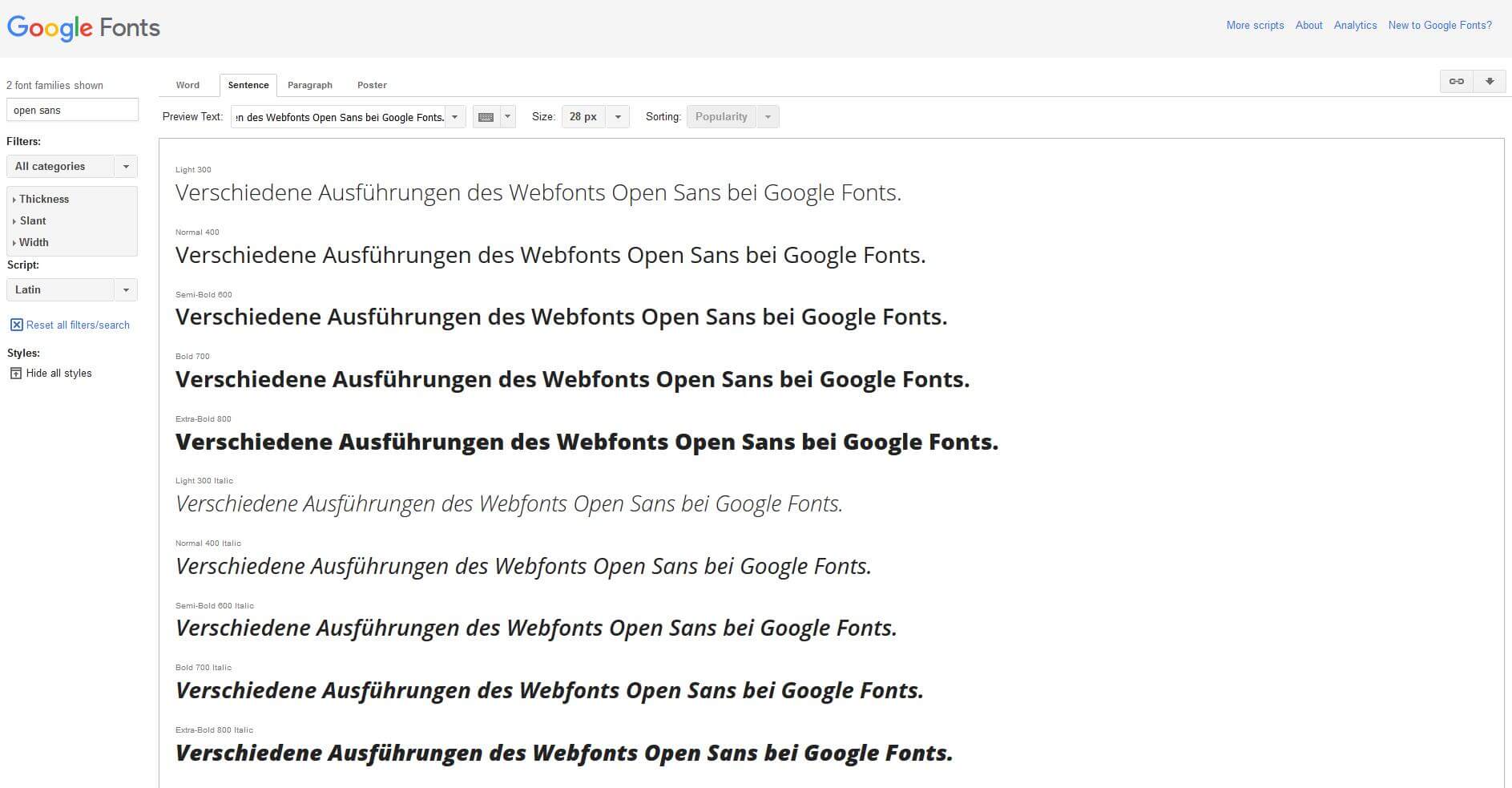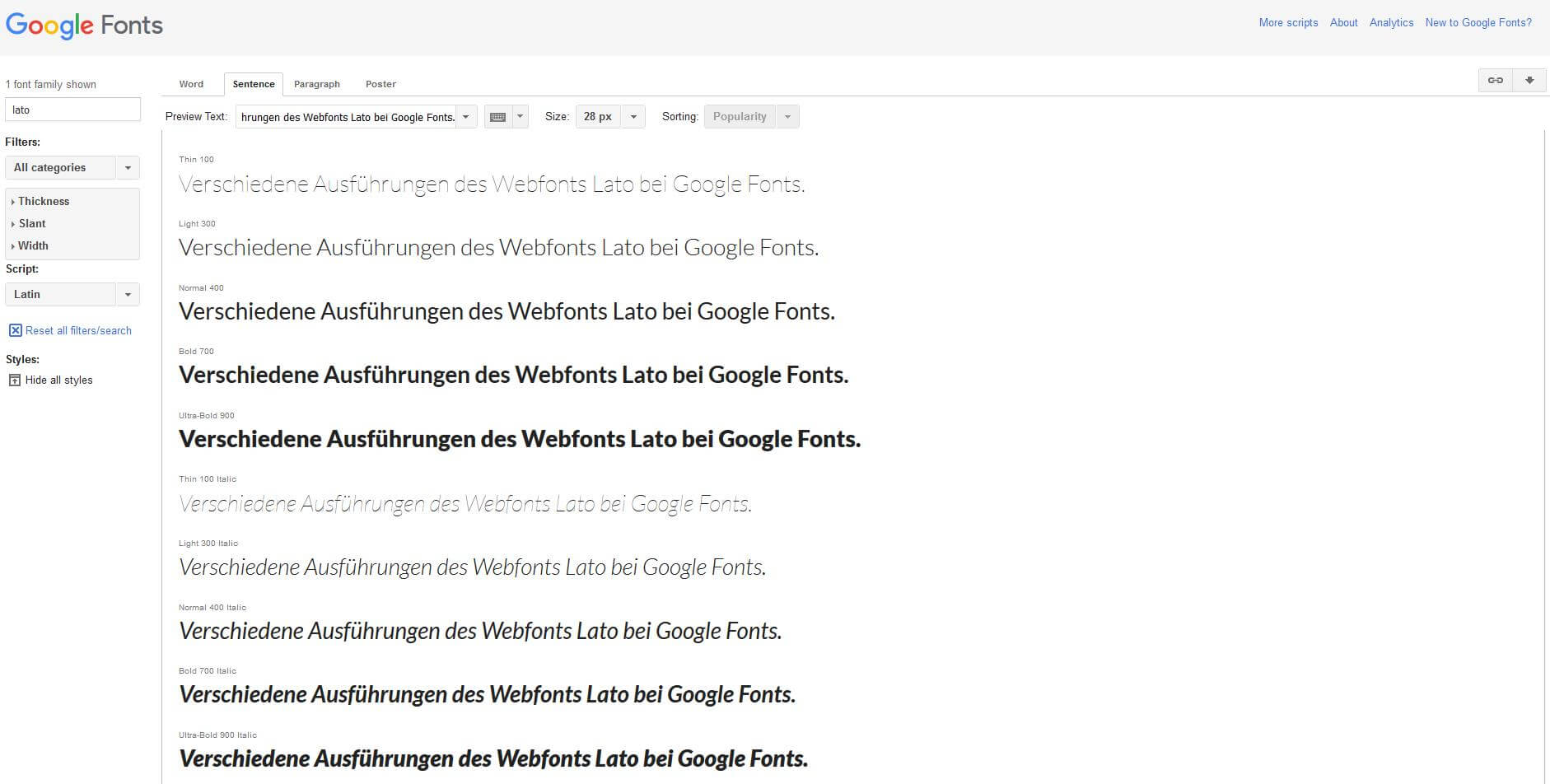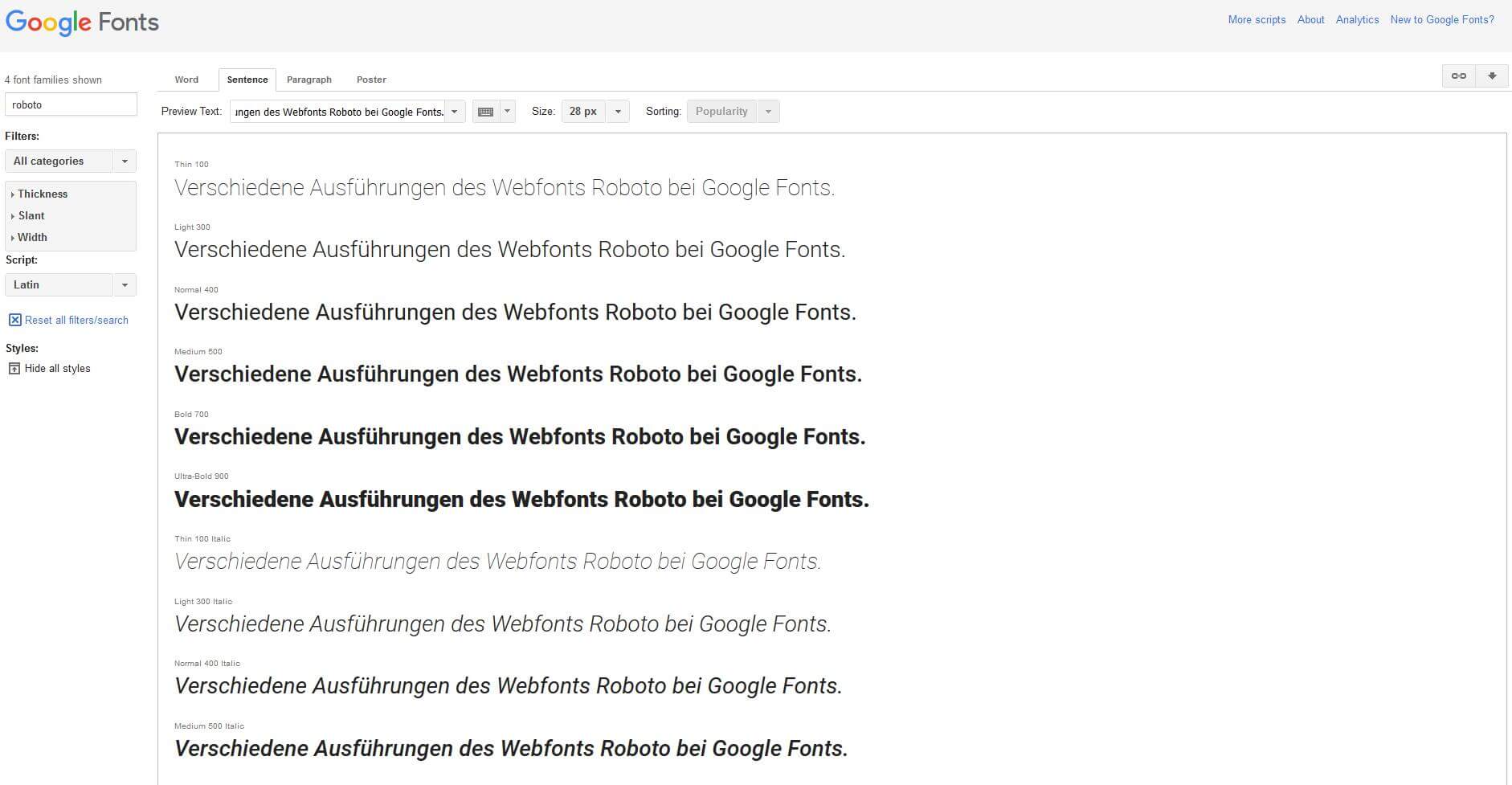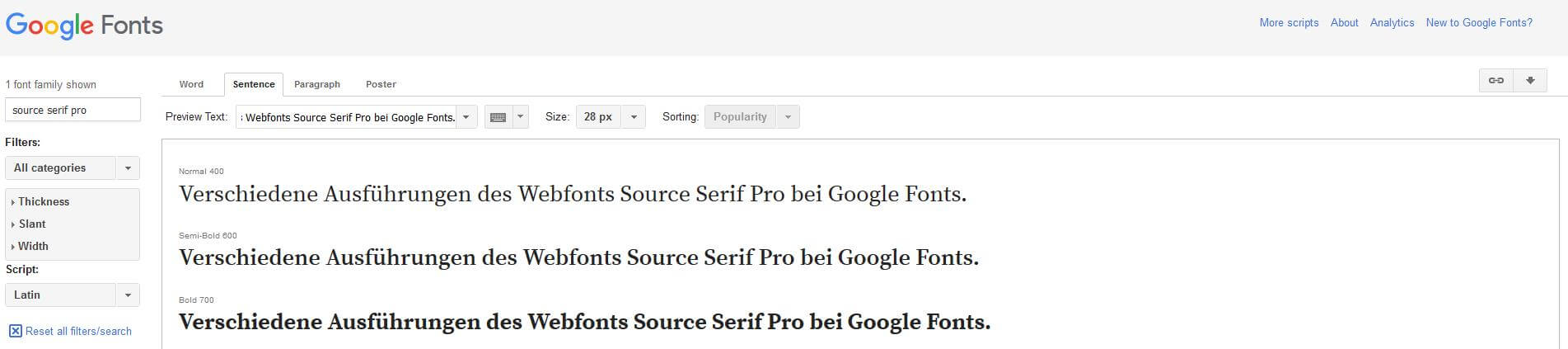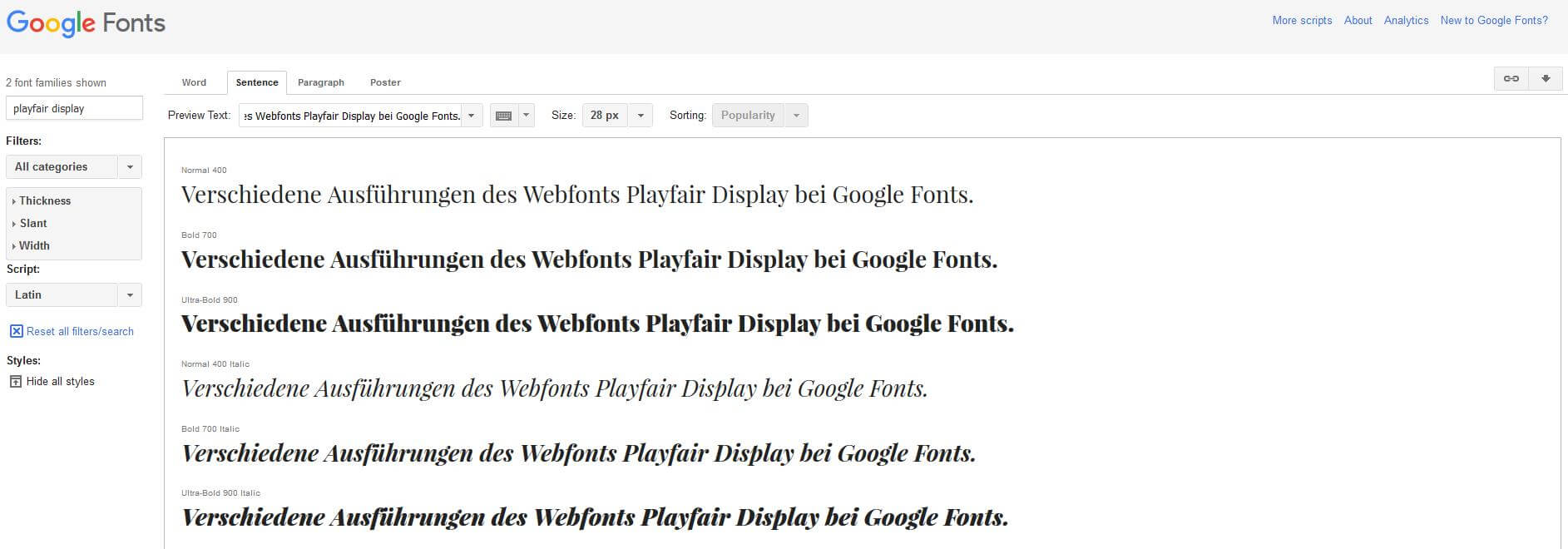
Typografie im Responsive Webdesign - Teil 2: Geeignete Schriftarten
Wenn Sie eine Schrift für Ihre responsive Website suchen, können Sie sich aus dem reichhaltigen Angebot an sogenannten responsiven Webfonts (reaktionsfähigen Schriften für Internetseiten) im Netz bedienen.
Kostenlose Webfonts fürs Responsive Webdesign
Webfonts eignen sich als Grundlage für die Typografie im Responsive Webdesign, da sie auf Vektorgrafiken basieren, die frei skalierbar sind. Beim Aufruf einer Webseite, die Webfonts verwendet, werden die Schriften von einem Server heruntergeladen und anschließend zur Anzeige im Webbrowser des Users umgesetzt. Reaktionsfähige Webfonts passen sich hierbei den Anforderungen des jeweiligen Browsers bzw. Anzeigegeräts an. Diverse Internet-Plattformen halten responsive Webfonts zum Download bereit – teils gratis, teils kostenpflichtig. Bekannte Anbieter von gebührenpflichtigen Schriftarten sind beispielsweise Adobe Fonts oder Fontspring, die mit einer großen Auswahl an bekannten Schriftarten, darunter vielen Klassikern, aufwarten.
Genauso können Sie aber auch auf das nicht weniger vielfältige Angebot an kostenfreien Webfonts zurückgreifen. Sammlungen freier Webfonts finden Sie z. B. bei Google Fonts, Font Squirrel oder DaFont. Nicht alle dort erhältlichen Schriftarten eignen sich für den allgemeinen Gebrauch: Einige sind zu verspielt oder ungewöhnlich und deshalb nur für spezielle Belange zu empfehlen; manche enthalten keine Umlaute oder andere Sonderzeichen – generell variiert der Zeichenumfang der Schriftarten, teilweise stark. Achten Sie daher darauf, dass Sie für Ihr Responsive Webdesign eine Schrift auswählen, die ausreichend viele Zeichen umfasst. Exemplarisch stellen wir Ihnen einige vielseitig einsetzbare Google Fonts für Ihre Website vor.
Webtypografie-Beispiele von Google Fonts
Die Plattform Google Fonts wird von vielen Webdesignerinnen und -designern als Quelle von Schriften für eine reaktionsfähige Typografie genutzt. 2010 ging die Seite online. Von Anfang an wurden ausschließlich kostenlose Open-Source-Fonts angeboten, die sowohl für nichtkommerzielle als auch für kommerzielle Zwecke genutzt werden dürfen. Sie haben die Auswahl aus über 1.900 verschiedenen Webfonts. Alle Fonts können Sie herunterladen und über einen Code in Ihren Webauftritt einbetten.
Open Sans
„Open Sans“ gehört zu den klassischen Standard-Webfonts. Es handelt sich um eine serifenlose Schrift mit klassischem, schlichtem Erscheinungsbild. Sie wurde von Steve Matteson entworfen und ist für die Nutzung im Web, für mobile Geräte und für den Printbereich optimiert.
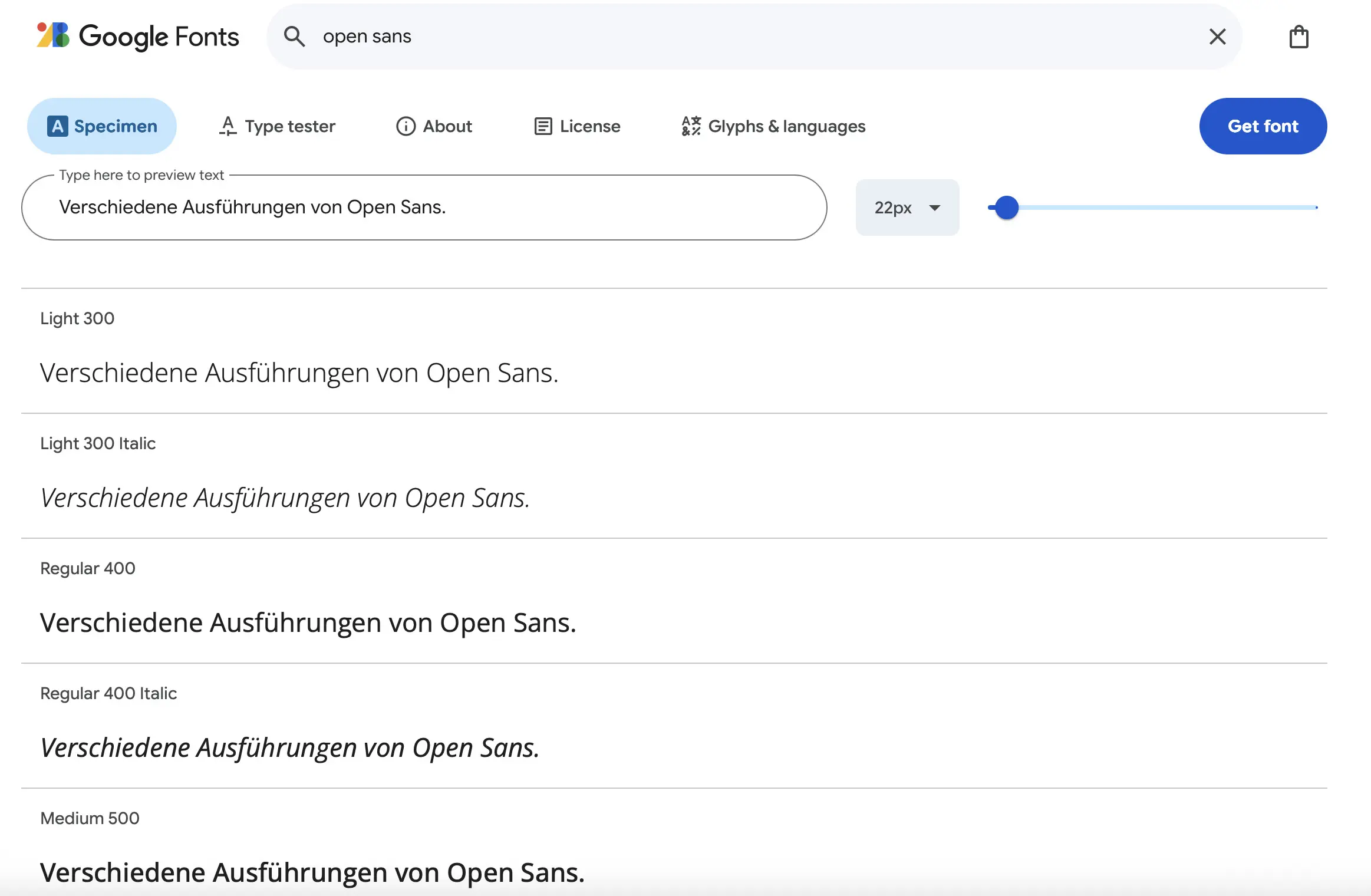
Lato
„Lato“ ist eine weitere populäre Schriftart ohne Serifen. Sie wurde von Łukasz Dziedzic entwickelt und mit der Unterstützung von Google veröffentlicht.
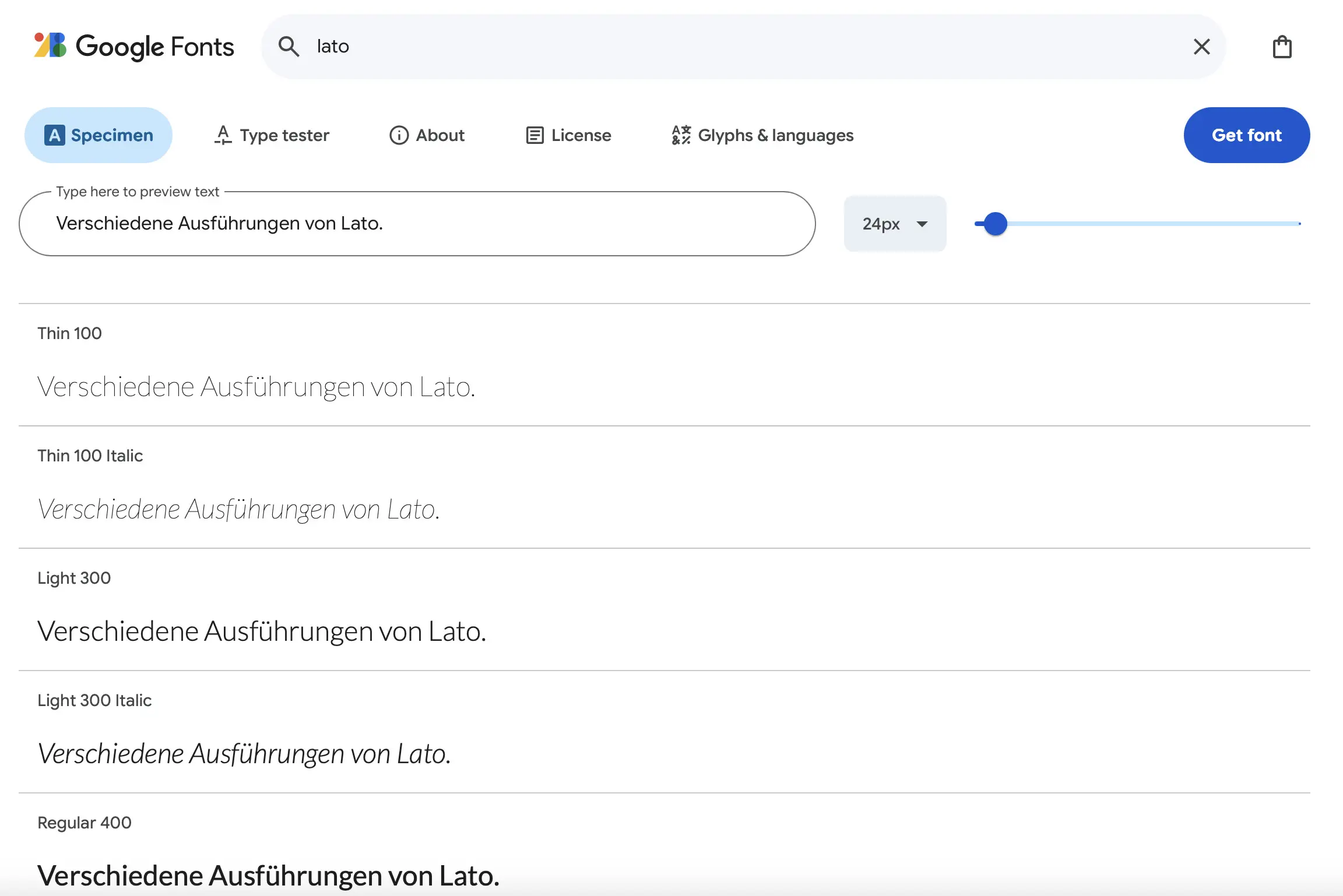
Roboto
„Roboto“ wurde zunächst als Schriftart für das Betriebssystem Android genutzt und seitdem kontinuierlich weiterentwickelt. Der ebenfalls serifenlose Webfont besteht aus relativ schmalen Buchstaben, wodurch mehr Zeichen in eine Zeile passen als bei vielen anderen Schriften.
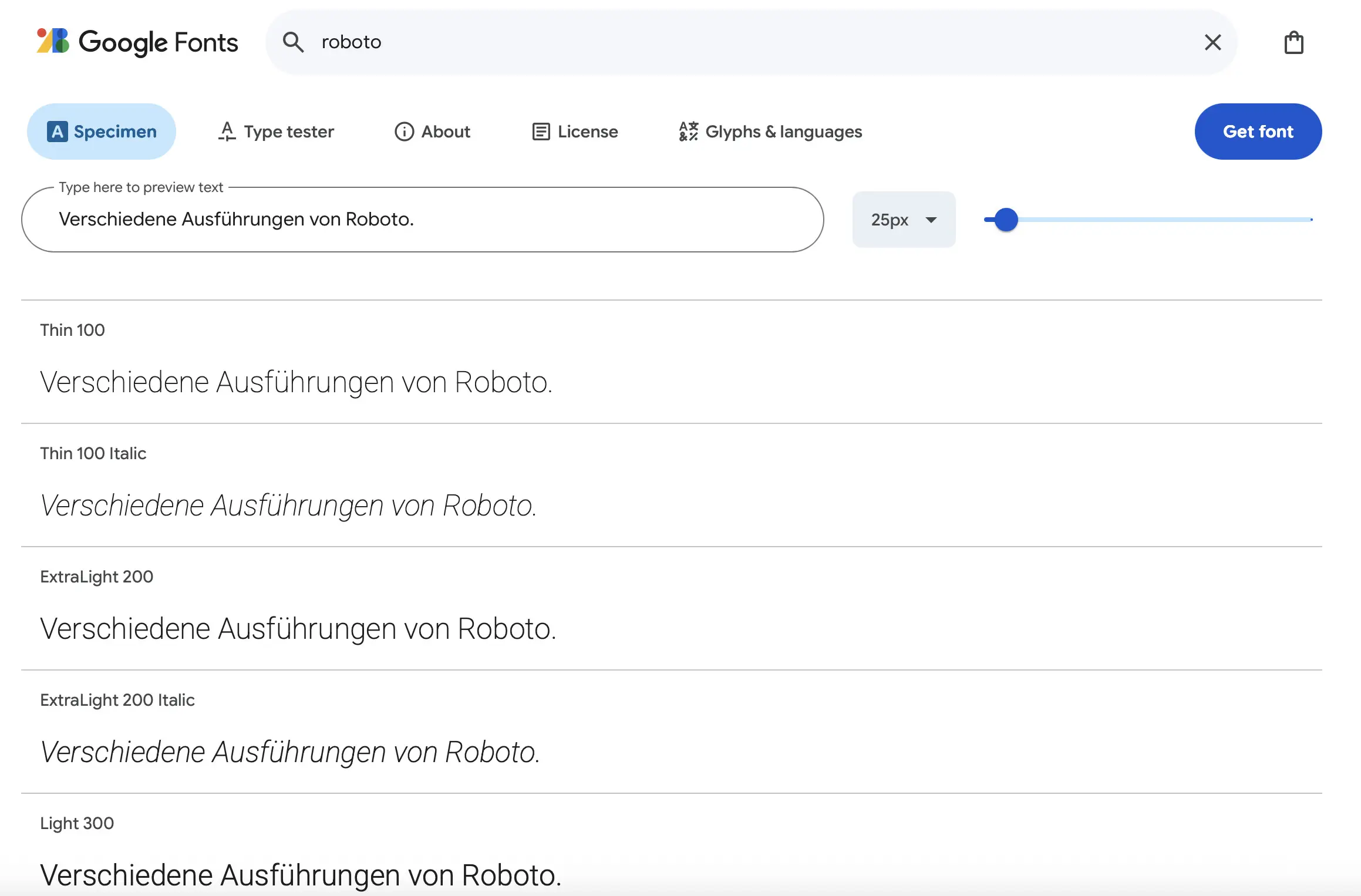
Source Serif 4
„Source Serif 4“ ist eine von Adobe entwickelte Schriftart, die Bestandteil der Source-Fontfamilie ist. Die Serifenschrift kann als Ergänzung zum serifenlosen Font „Source Sans 3“ und der Monospace-Schrift „Source Code Pro“ dienen, die Adobe ebenfalls kostenfrei bereitstellt.
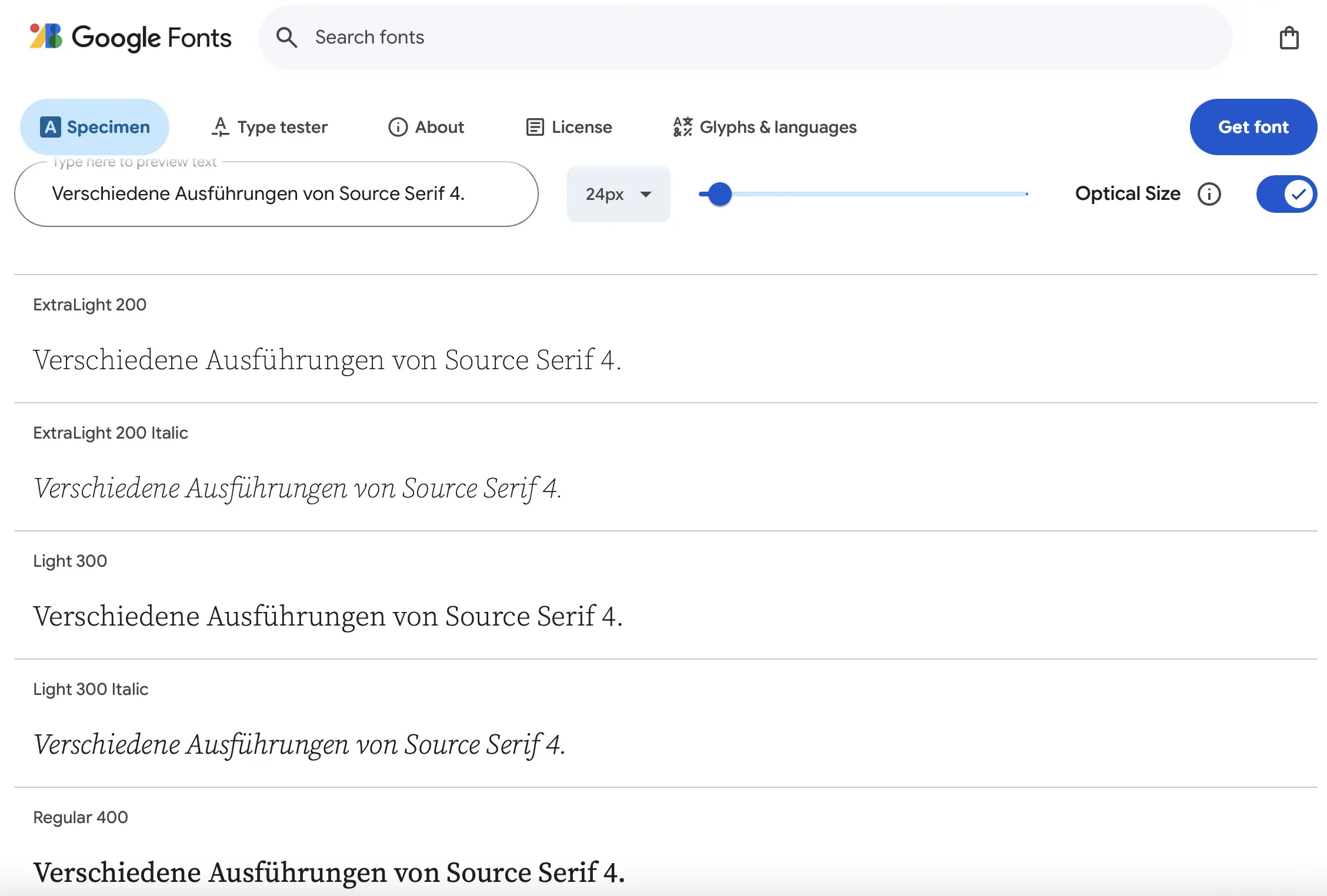
Playfair Display
Wenn Sie auf eine stilvolle Schrift mit Serifen zurückgreifen möchten, ist der Webfont „Playfair Display“ eine gute Wahl. Sie können zwischen verschiedenen Stilen der eher dekorativen Schrit wählen.
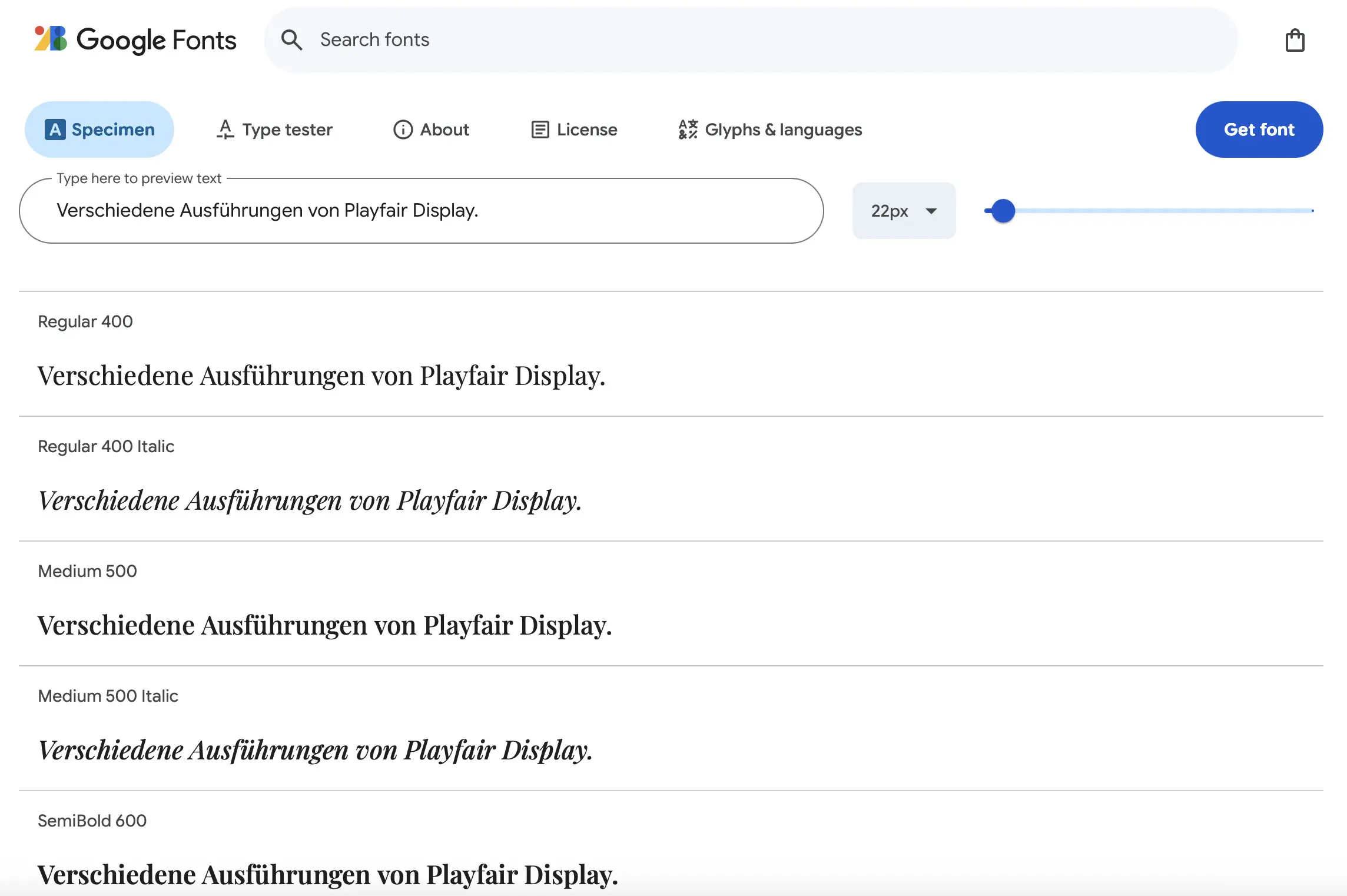
- Geben Sie im Suchfeld „Open Sans“ ein und wählen Sie die Schriftart. Dort klicken Sie auf den Button „Get font“.
- Daraufhin werden Ihnen noch einmal die wichtigsten Informationen zum Webfont angezeigt. Mit einem Klick auf den Button „Get embed code“ fahren Sie fort.
- Nun wird Ihnen je ein Code für den
<head>Ihrer Webseiten und für das CSS-Dokument angezeigt. Sie haben außerdem die Möglichkeit, den gewünschten Stil der responsiven Schrift einzustellen. - Um „Open Sans“ in HTML einzubinden, fügen Sie im
<head>den entsprechenden Code (der auch den Link zu Google Fonts enthält) ein. Die Anweisung sieht dann so aus:
</html>htmlMit dem zweiten Code definieren Sie die Schrift in CSS:
/ *Schrift anwenden – Beispiel für Open Sans* /
font-weight: 400; / *Normales Gewicht* /
}cssWie Sie sehen, ist das Einfügen eines Webfonts über den Google-Service ausgesprochen simpel. Neben dieser Variante können Sie bei Google Fonts außerdem die @import-Regel in CSS nutzen, um die Schrift einzubinden.
Fazit: Fürs Responsive Webdesign gibt es viele gute Schriften gratis
Für anpassungsfähige Webseiten steht eine breite Palette an Schriftarten zur Verfügung. So können Sie problemlos kostenfreie Webfonts von Google Fonts, Font Squirrel u. a. verwenden. Allerdings sollte Ihnen auch bewusst sein, dass gerade die beliebten Schriften wie „Open Sans“, „Roboto“ oder „Lato“ sehr häufig im Web benutzt werden. Eine besonders individuelle, gar einzigartige Schriftart (etwa im Sinne einer Hausschrift) erhalten Sie nicht als kostenlosen Webfont. Dafür gestatten Ihnen die frei verfügbaren Schriften einen sehr großen Freiraum bei der responsiven Webtypografie. Außerdem ist die Einbindung in die Webseite schnell erledigt – so profitieren Ihre Besucherinnen und Besucher innerhalb kürzester Zeit von reaktionsfähigen Webfonts.